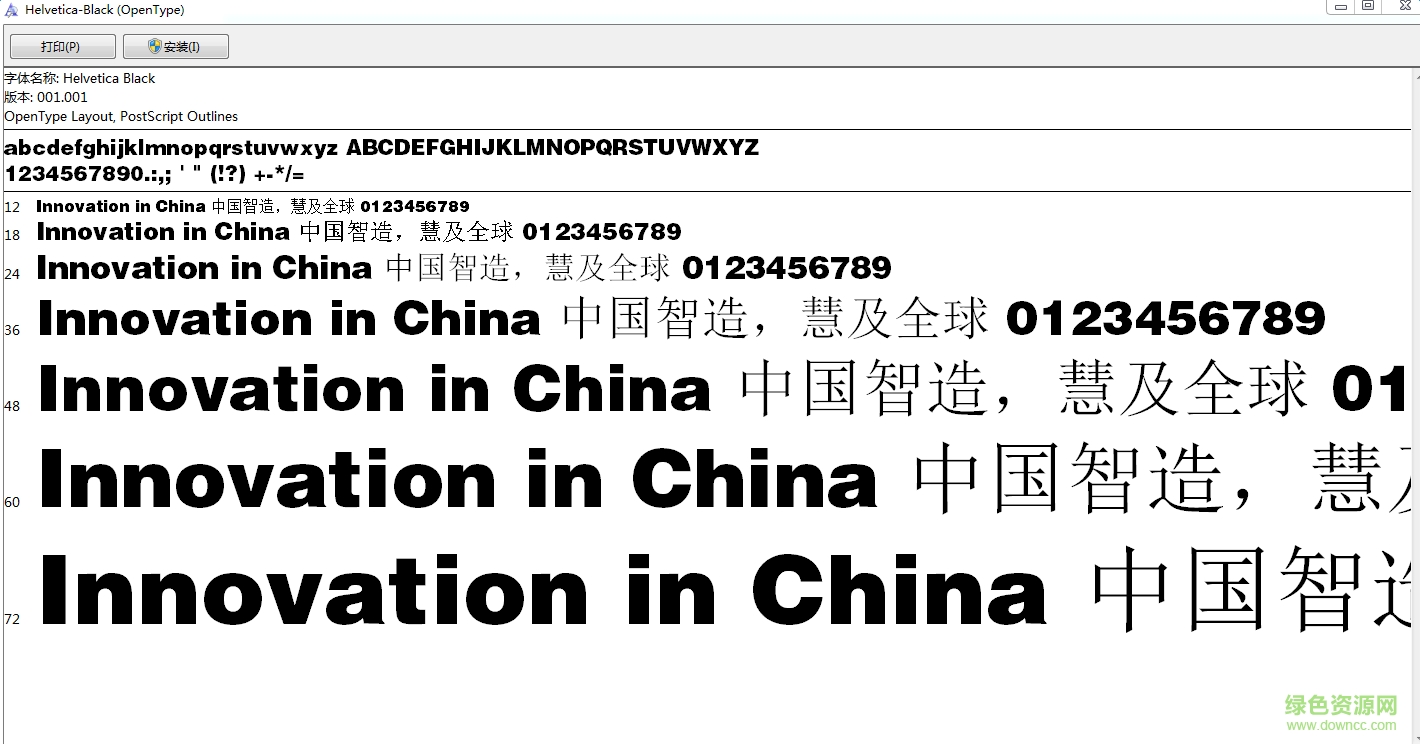
helvetica black字體是helvetica字體中較粗的一款,該字體結(jié)構(gòu)簡(jiǎn)潔,筆畫粗細(xì)變化微弱,易讀性很高,有需要者歡迎在綠色資源網(wǎng)下載!
Helvetica是全世界使用最廣泛無(wú)襯線字體, 由瑞士設(shè)計(jì)師 Max Miedinger 于 1975 年設(shè)計(jì). 是一款已經(jīng)超過(guò)50年歷史的字體,在設(shè)計(jì)界的地位似乎無(wú)人能敵,是世界上最受認(rèn)可的字體,一直被廣泛使用,人們甚至為這款字體拍攝了一部紀(jì)錄片。不管你喜不喜歡,這款字體以獨(dú)特,專業(yè),永不過(guò)時(shí)而得到眾人的青睞。Helvetica 擁有多種風(fēng)格,多個(gè)版本,世界上使用它設(shè)計(jì)成著名Logo多不勝數(shù),有航空公司,汽車公司,以及微軟這樣的軟件巨人。